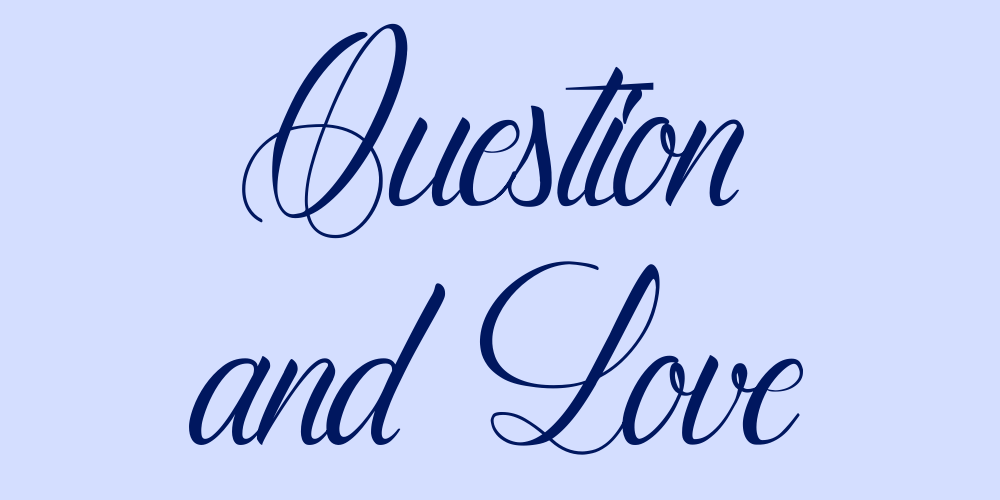
Olá! Estou buscando uma fonte elegante para adicionar estilo ao seu design? A fonte “Question and Love” é perfeita para os criativos que querem um toque de sofisticação em seus projetos, seja eles pessoais ou comerciais. Sua designer, Hamilton, criou esta fonte com a intenção de tornar suas mensagens mais expressivas e emocionantes. O nome “Question and Love” é uma abordagem original e intrigante que captura os elementos complementares da elegância do amor e as perguntas que levam ao conhecimento. Esta fonte não apenas oferece um design atraente, mas também permite que você personalize sua mensagem de maneiras diferentes. Se você está planejando usar esta fonte em qualquer projeto comercial, por favor, entre em contato conosco primeiro para garantir seu uso legal e o direito de copiar. A fonte “Question and Love” é um presente para seus projetos de design, tornando suas criações ainda mais especiais. Não importa se você está trabalhando com uma imagem, texto ou até mesmo um layout gráfico, a “Question and Love” pode ajudar a destacar sua arte. Seja qual for o seu projeto, certifique-se de ter essa fonte em seu arsenal de recursos para dar vida e emoção a seus projetos.